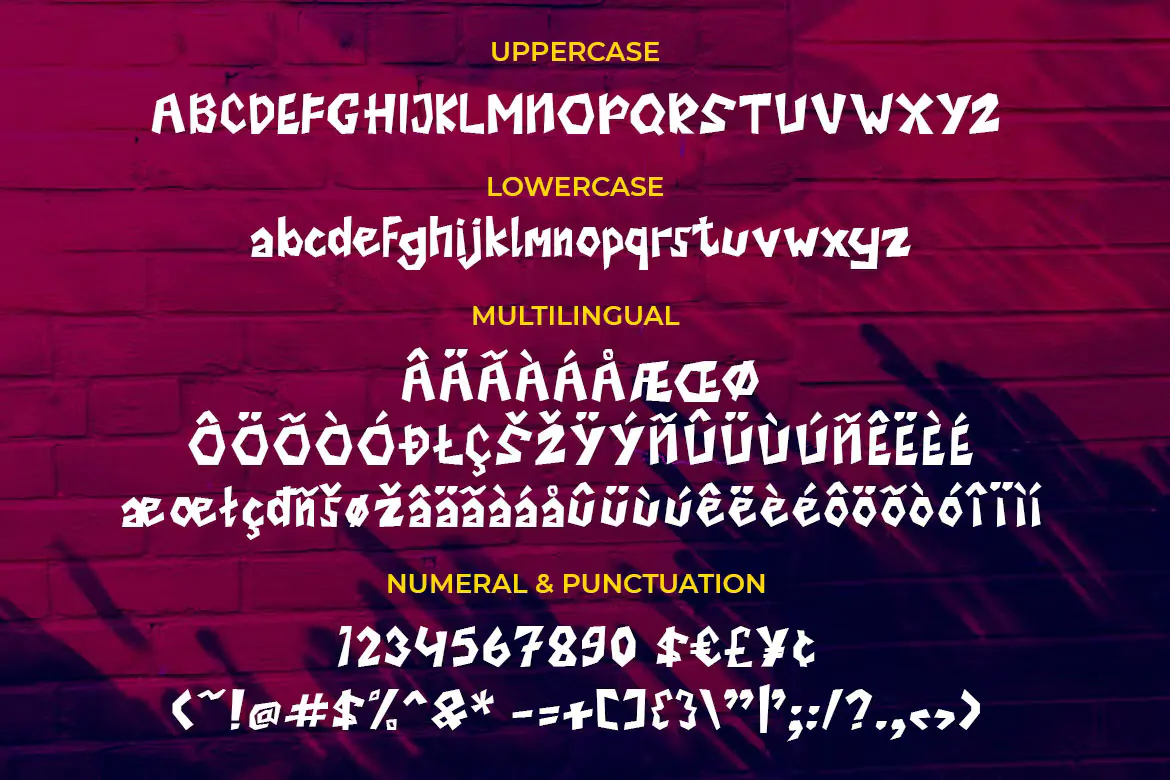
فونت دیوار نویسی Grande
فونت دیوار نویسی و گرافیتی
فونت دیوار نویسی و گرافیتی Grande یک اسکریپت فونت زیبا است که از آن میتوان در طراحی انواع پوستر، بنر، بسته بندی محصولات، چاپ تیشرت، ظروف یکبار مصرف و صدها مورد و پروژه دیگر استفاده نمود.